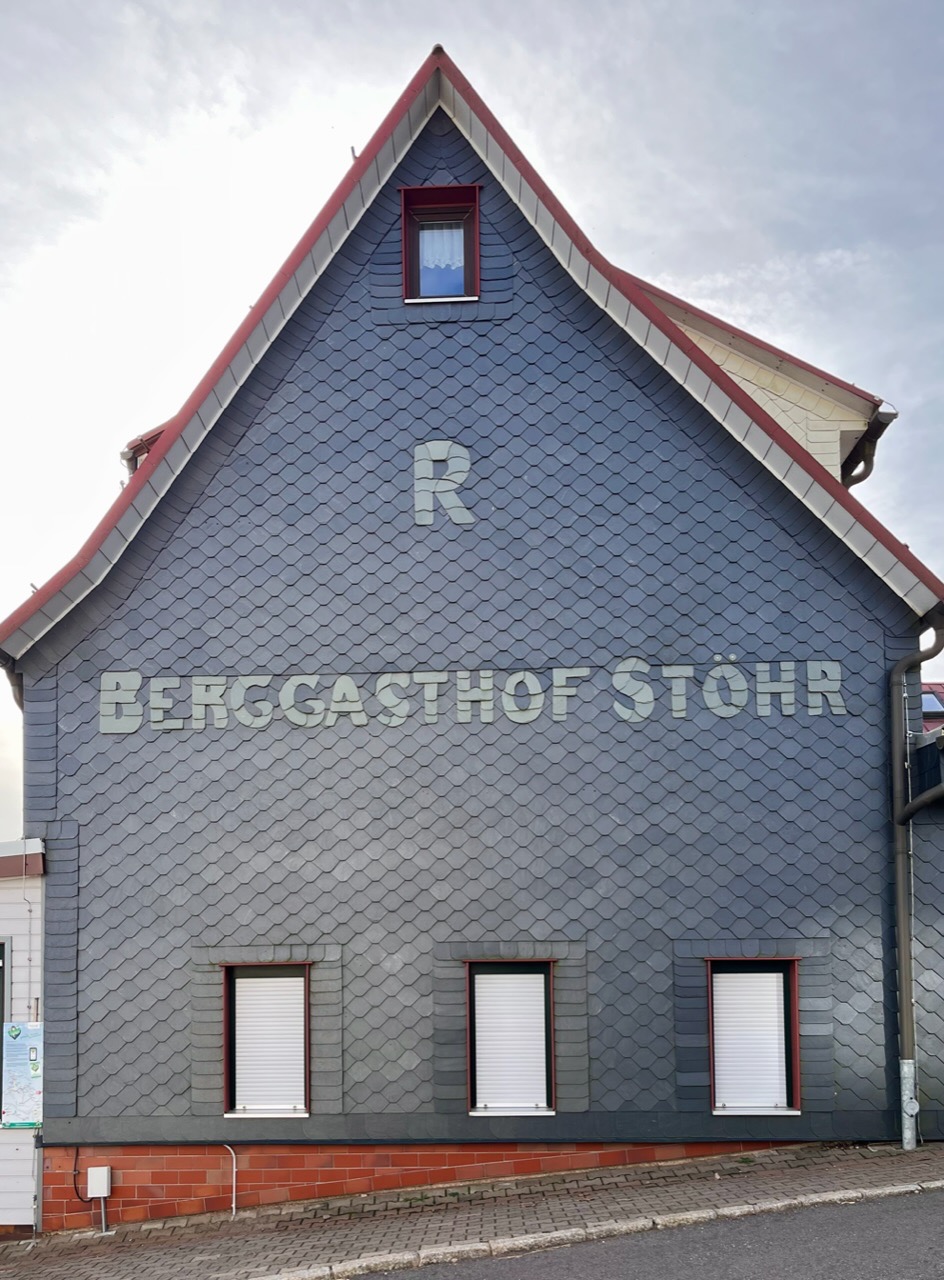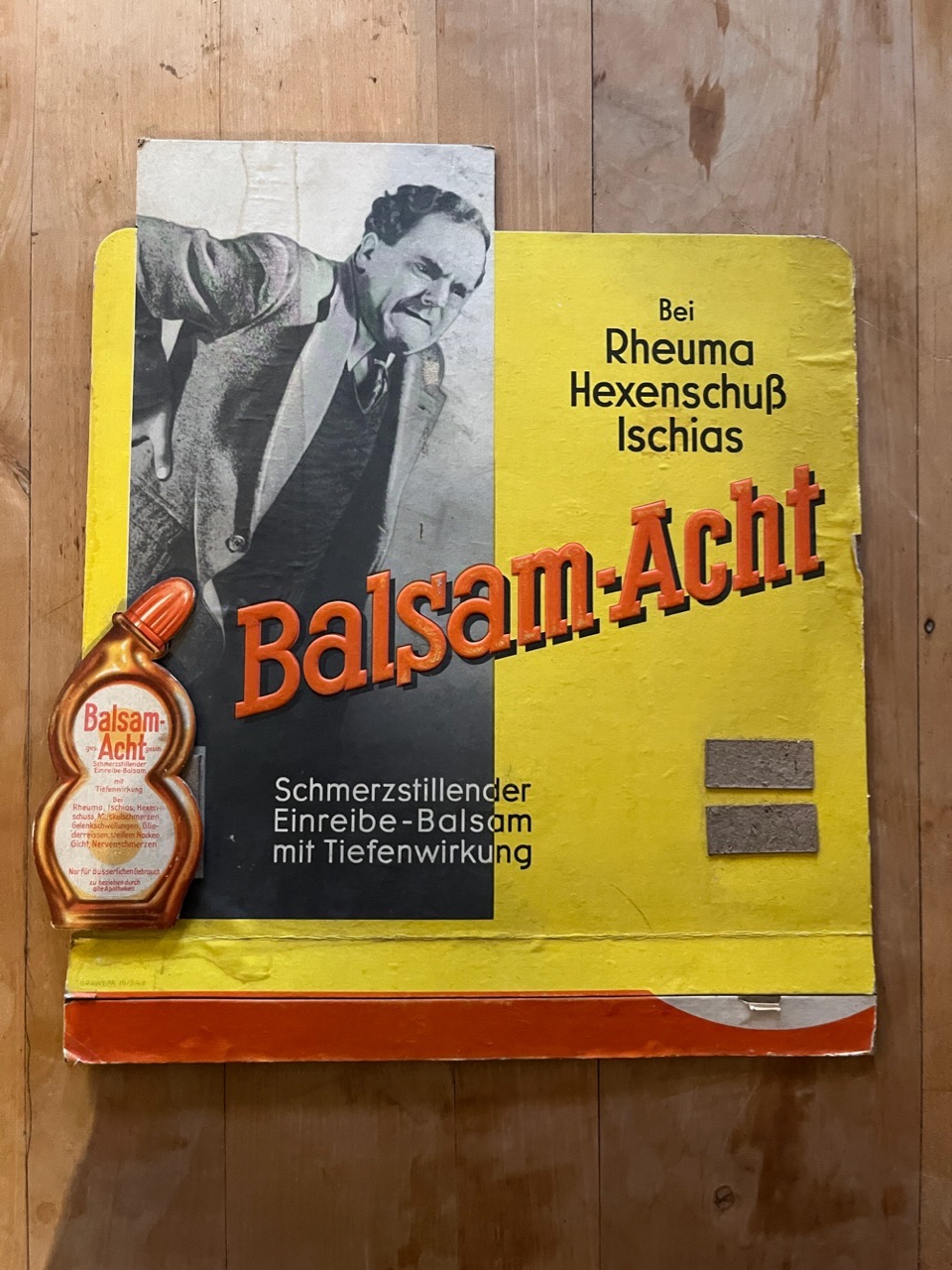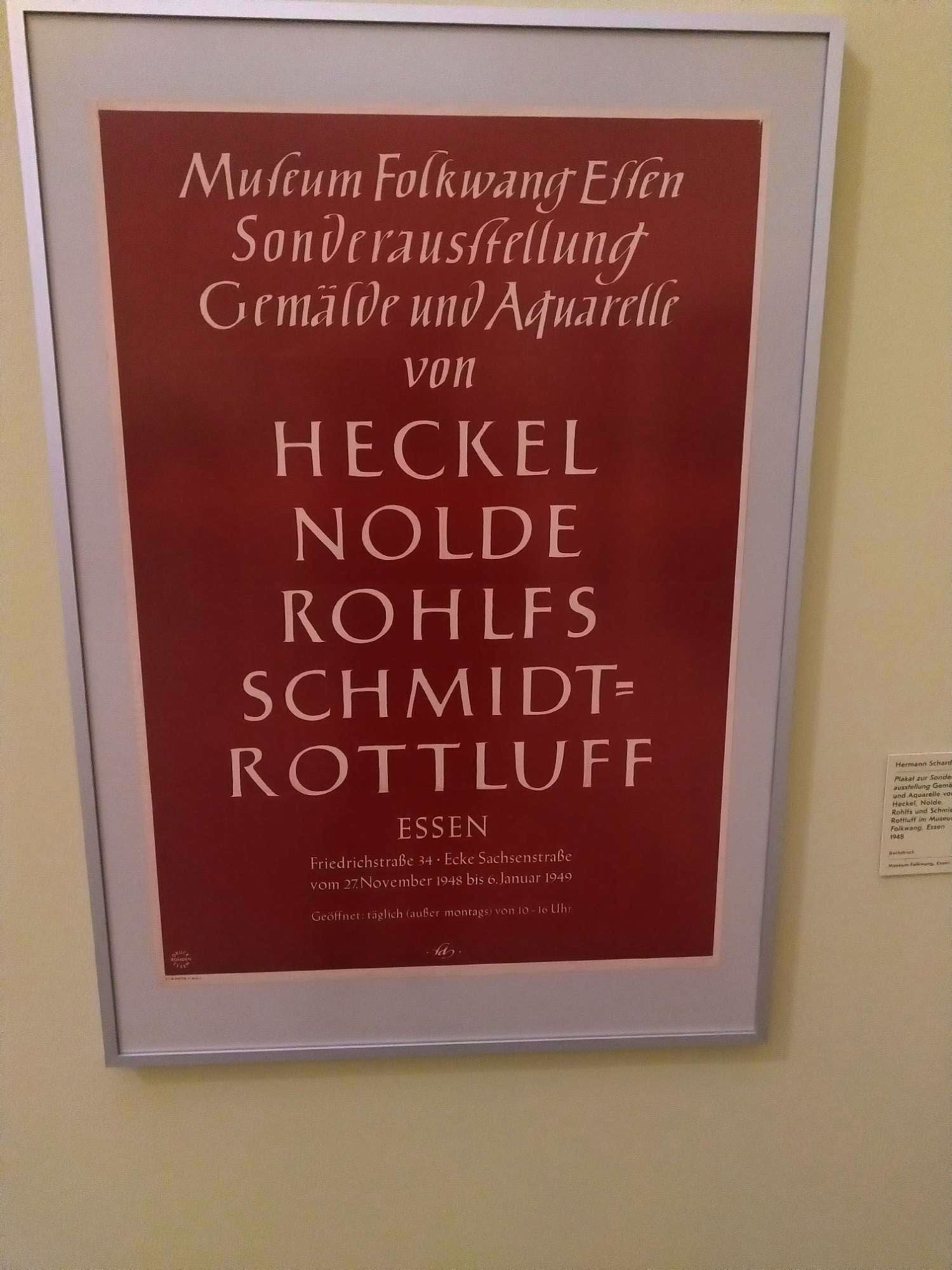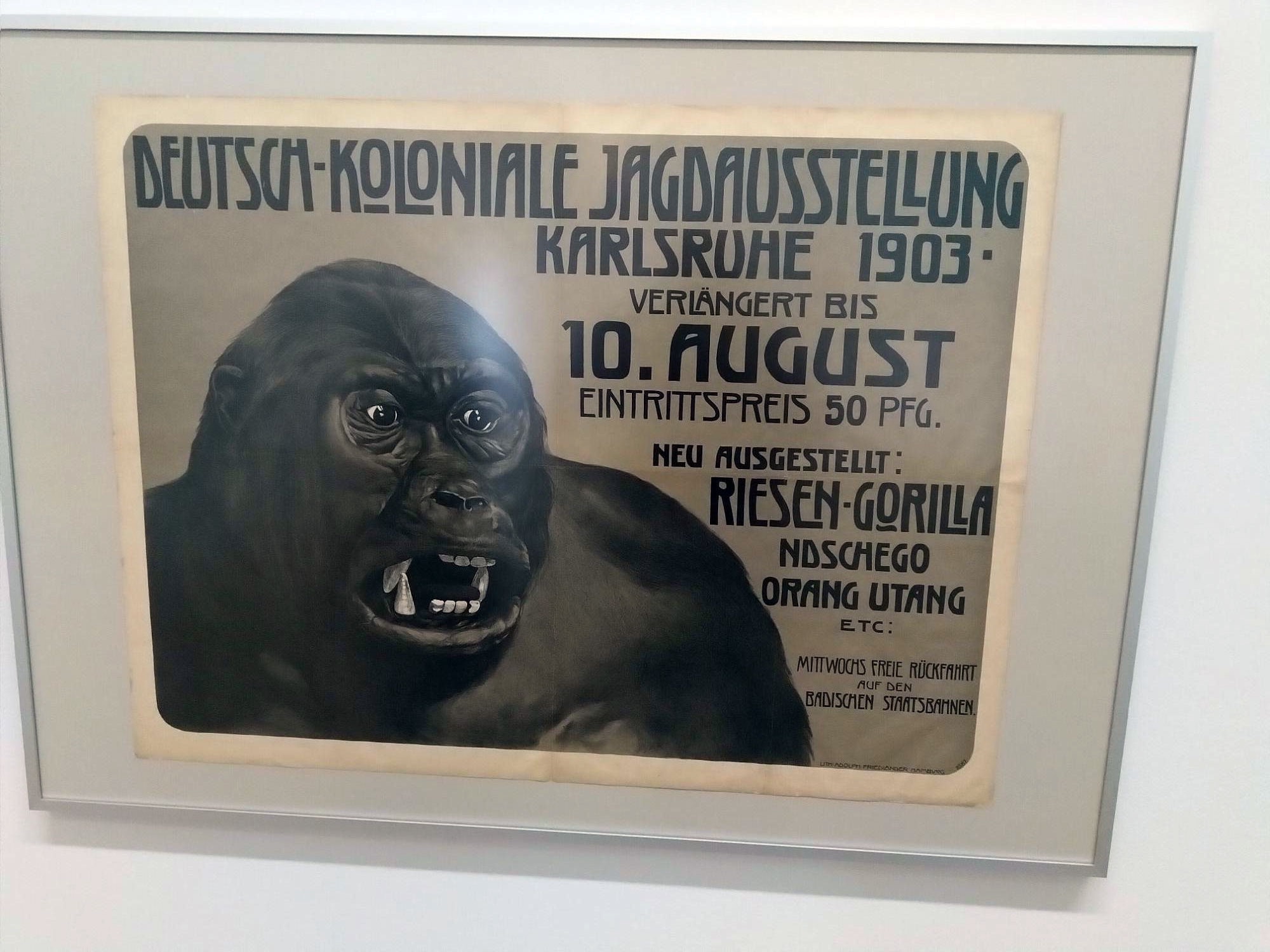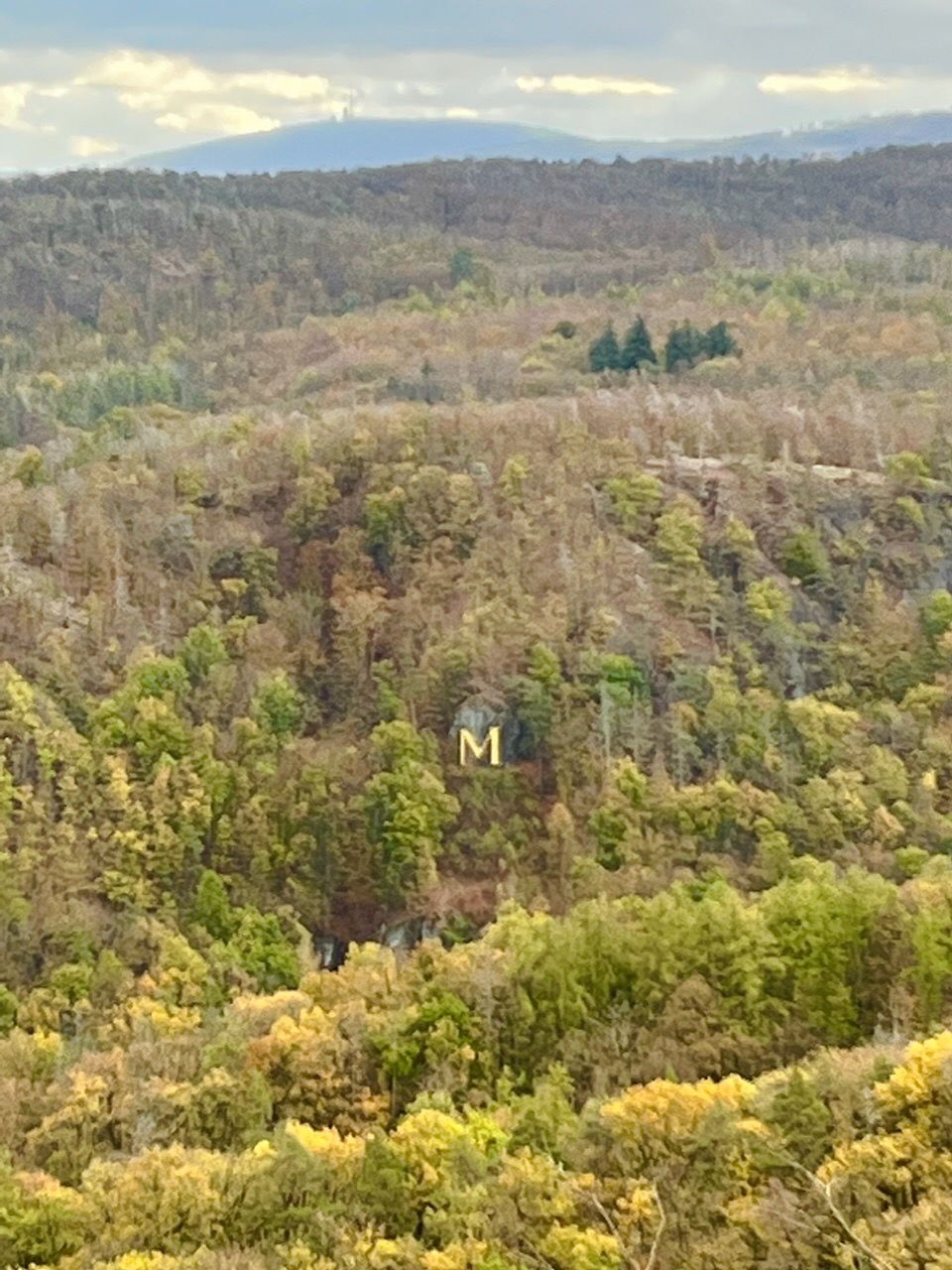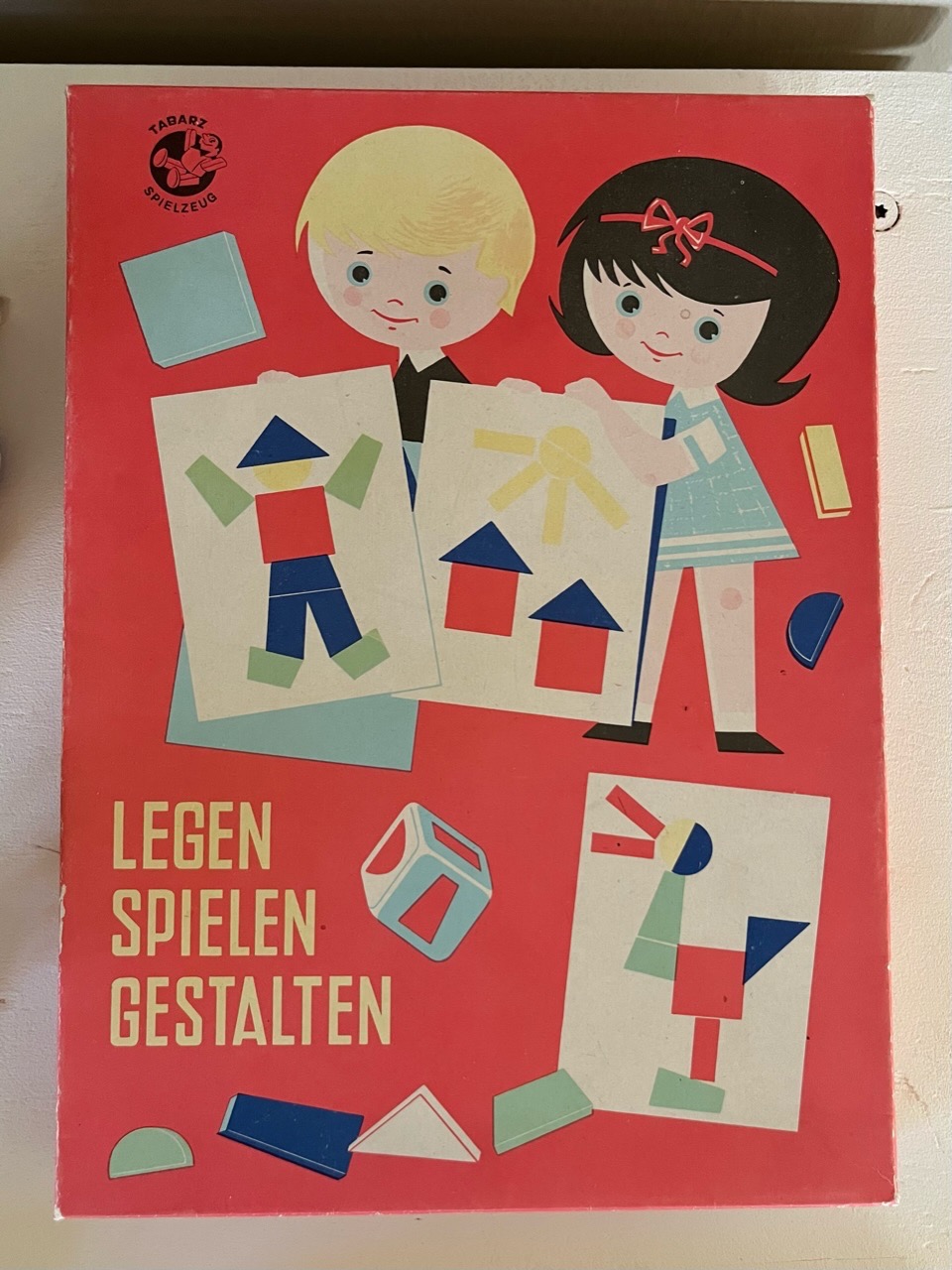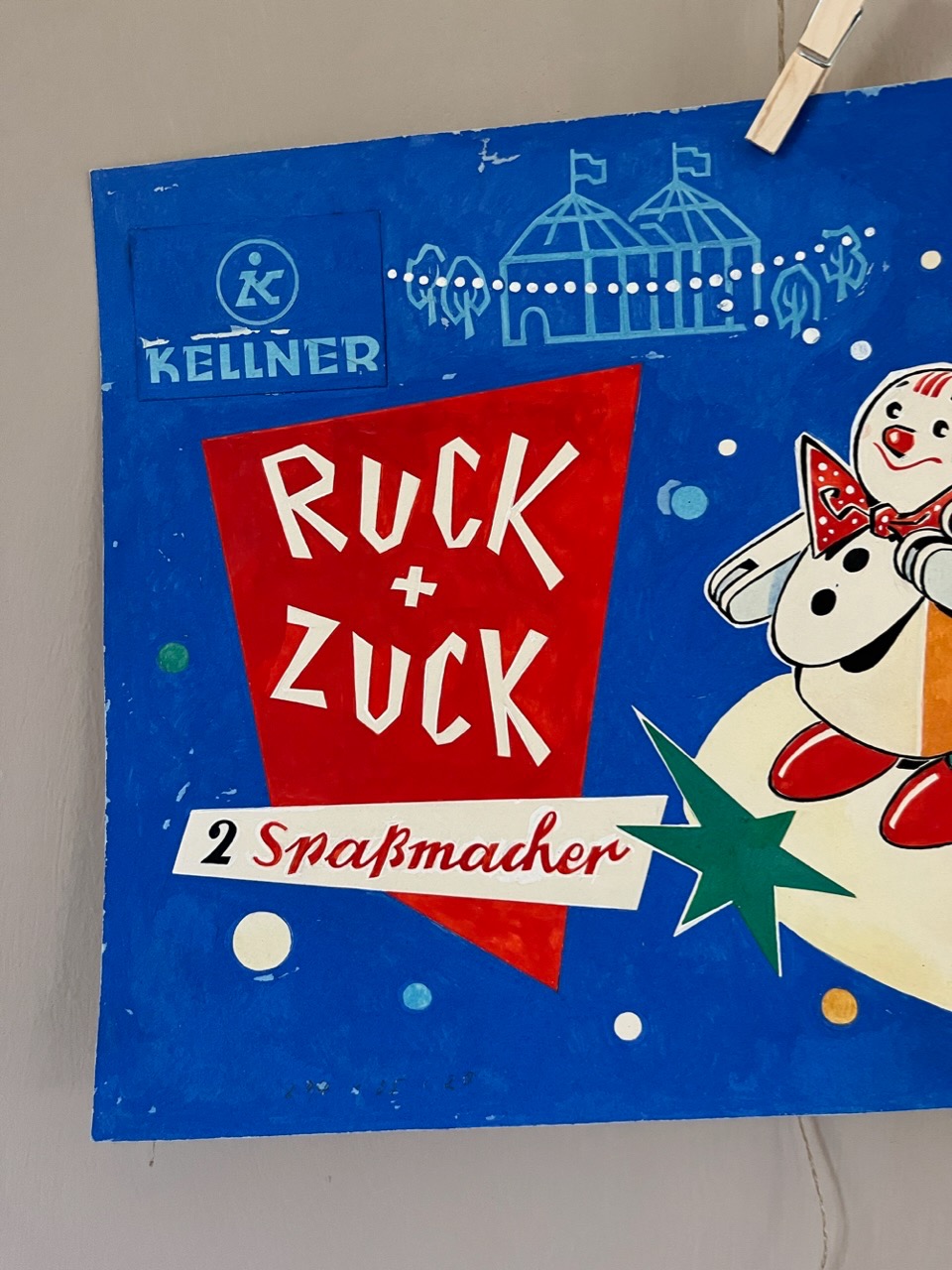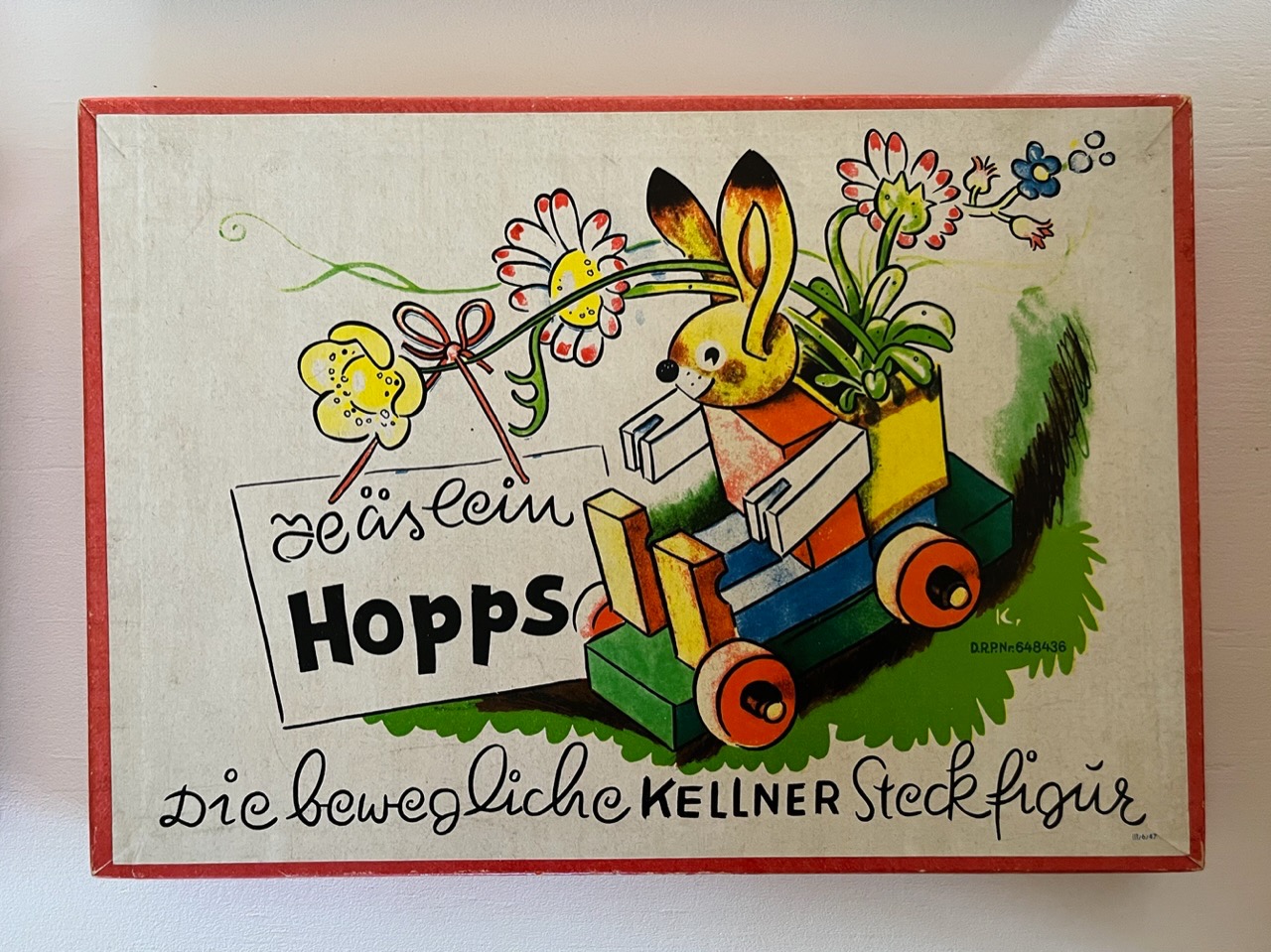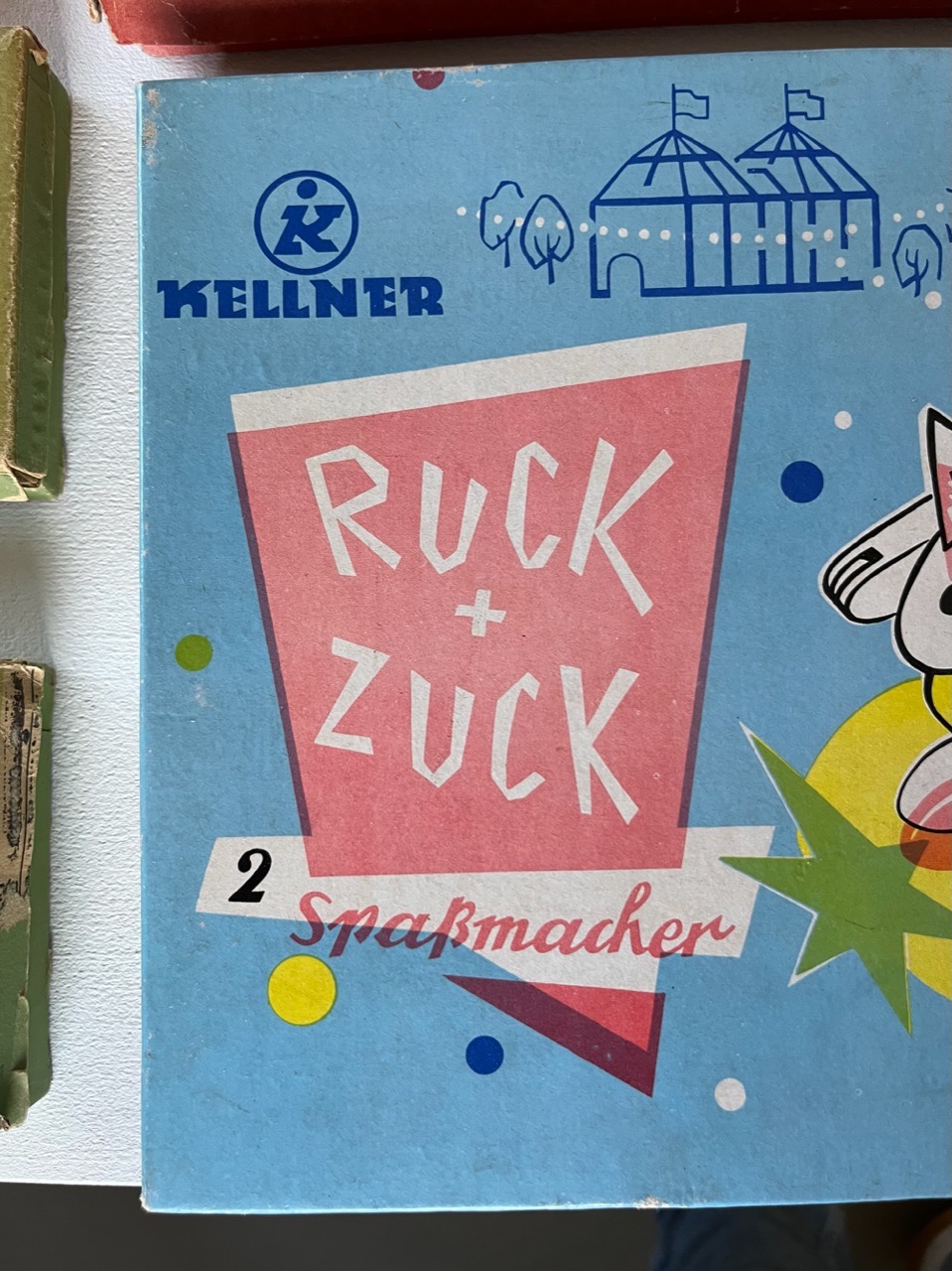
Auch wenn ich das Plakat zur Jagdtrophäen-Ausstellung sehr gruselig finde, ist der graphische Umgang mit dem L grandios.
OT: Ich hab gerade einen nostalgischen Moment – Ende der 60er (im Westen, wohlgemerkt) bekam ich einen Hasen Hopps von Kellner, an den denke ich noch heute oft (z.B. wenn ich mir ein neues Bastelbuch ausdenken soll) …
»Magnum«-Werbung?
Da hat sich aber jemand redlich Mühe gegeben, die Handschrift wie Sütterlin aussehen zu lassen...
Was erinnert dich denn dabei an Sütterlin? An der Schrift ist doch nichts Zackig-Eckiges; ganz im Gegenteil: die ist sowas von rund. Da sehe ich nicht den leisesten Anklang an Sütterlin oder sonstige Deutsche Kurrentschriften.